Eric Gill, Adrian Frutiger 和 Max Miedinger是我们每天在用的字体的作者们,这些字体可以说都是不会轻易过时的优秀作品。这里收录了25个在设计领域里最普遍也最具时代性的字体,保证能让设计师用一辈子。
Helvetica
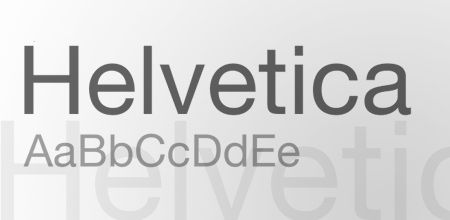
设计师哪个不认识Helvetica? 瑞士设计师 Max Miedinger 以及 Eduard Hoffmann 的作品。
Bodoni
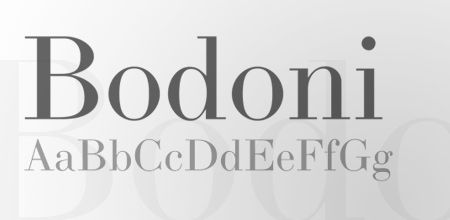
Giambattista Bodoni 1798年设计的有衬线字体,被Goodfellas gangster用来做电影海报。
Clarendon
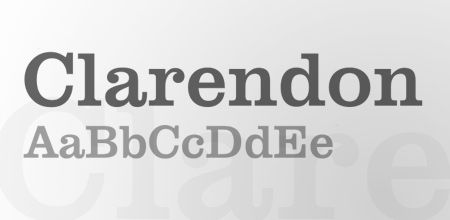
Robert Besley 1845年的设计。
Akzidenz Grotesk
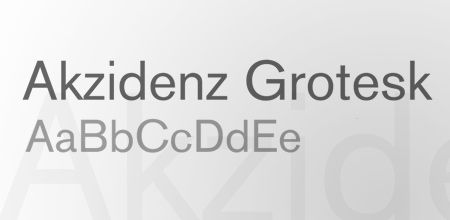
Helvetica的灵感来源,作者是Akzidenz Grotesk,1896年的作品。
Avenir
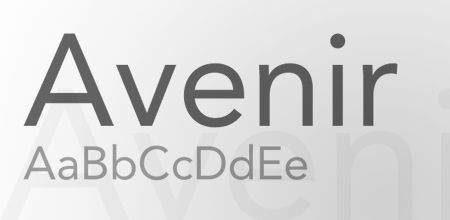
Adrian Frutiger的作品,这名字很熟悉吧?
DIN
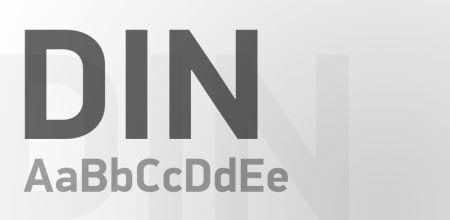
Albert-Jan Pool 1995年的作品,与其他的字体相比之下来得比较新。
Futura
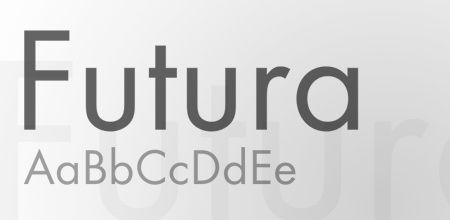
20年代 Paul Renner 的作品,被许许多多的公司用来做成logo。
News Gothic
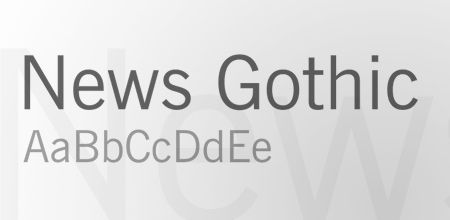
Morris Fuller Benton 1908年的作品,被电影 StarWars 用作开场 credits 的字体。
Frutiger
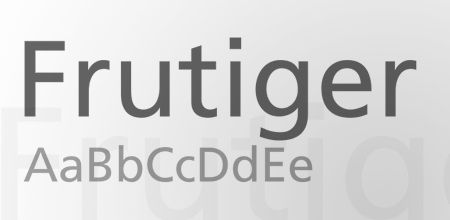
刚刚说道的 Adrian Frutiger 的另外一个作品。
Meta
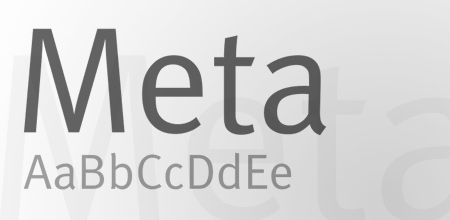
1986年 Erik Spiekermann 的作品。
Gill Sans
Eric Gill 1926年的作品, 伦敦 Underground的看牌用的就是这个字体。
Garamond
可以说是最有名的有衬线字体。很多时候被用来当成书本内容的字体,笔者的最爱。
Mrs Eaves
Zuzana Licko 1996年设计的有衬线字体。
Dax
UPS常用的字体,Hans Reichel 作品。
Myriad
打开Abode都会看到的字体,是Rober Slimback以及Carol Twombly特地为 Adobe 设计的。
VAG Rounded
也称为 VAG Rundschrift, 1979年为 Volkswagen 设计的字体,许许多多的 Web 2.0 都用的这个。
Optima
Hermann Zapf 的作品,特点是细细的线条。
Avant Garde
Avant Garde 杂志使用的字体,现在许多的标题都喜欢用这个字体。
Univers
又是 Adrian Frutiger 的作品。常常会和 Helvetica 以及 Akzidenz Grotesk 搞混。
Rockwell
Monotype 1934年的作品。现在常常被用作抢眼的标题字体。
Minion